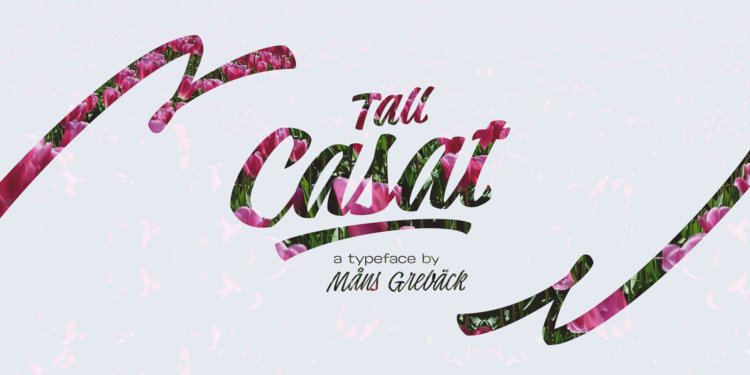
Introduzimos Tall Casat! Esta é uma família de tipos script atraente que destaca-se pela sua elegância e originalidade. Desenhada pelo designer Måns Grebäck durante 2017, esta fonte é um trabalho original de Måns Grebäck, criado em 2017. Seu conjunto completo de cinco pesos foi meticulosamente projetado para oferecer grande variação à família Tall Casat: Thin, Light, Med, Bold e Fat. O mais interessante sobre esta fonte são as múltiplas características do OpenType que ela inclui. Além das alternativas estilizadas, uma alteração alfabética com swashes e versões para inicial e final de todas as letras. Tanto os ornamentos quanto as ligaturas estão presentes. Com centenas de glifos disponíveis, Tall Casat apoia um amplo range de idiomas. Tal como a descrição original em inglês indica, a fonte é uma invenção interessante para quem deseja adicionar um toque criativo e único aos seus projetos digitais. Ela abrange desde pequenos detalhes estilizados até alterações alfabéticas com swashes, tornando-a uma escolha ótima para criar mensagens de impacto forte e personalizadas.